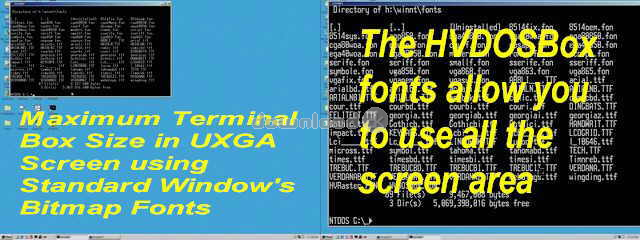
"Hallo-Visibility Font für Konsolenmodus."
HVDOSBox ist ein Windows-proportionalen Rasterbildschirmschrift. Es ist für alle, die Konsole Modus von Windows verwendet oder läuft MS-DOS-Anwendungen in einer Windows-Box. Die HVDOSBox Schriftarten bieten größere Lesbarkeit der Texte und viele weitere Punktgrößen als die Windows-Schriftarten geliefert. Die große Auswahl an Schriftgrößen ermöglicht ein Konsolenfenster, um dem Spiel die Größe des Monitors in jeder Auflösung skaliert werden. Die fontface auf ProCon Hallo-Sichtbarkeit HVFont die viel stärkeren Charakter Glyphen und besser lesbar Satzzeichen produziert basiert. Es verwendet eine modifizierte OEM-Codepage 437 Zeichen-Set. Normalerweise Leerzeichen - wie die binäre und ASCII NUL 255 - sind sichtbar, und der Raum Charakter kann als Gitter gezeigt, Programmierer und Screen-Designer mit Code-Layout und Design zu unterstützen.Bedarf Windows